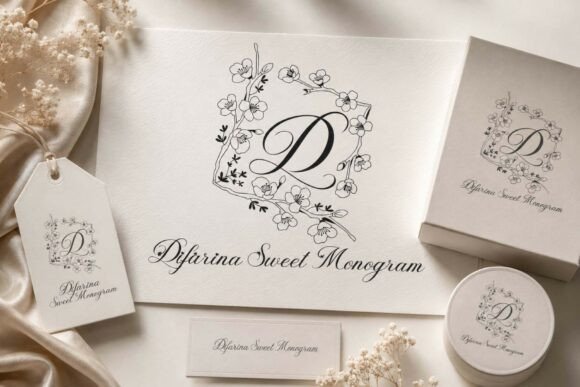
Difarina Sweet Monogram
Si vous recherchez des ressources de haute qualité comme Difarina Sweet Monogram, ce pack premium est un choix fantastique pour vos projets créatifs.
Que vous créiez des produits POD (impression à la demande), des invitations de mariage ou des visuels pour les réseaux sociaux, Difarina Sweet Monogram est un choix idéal.